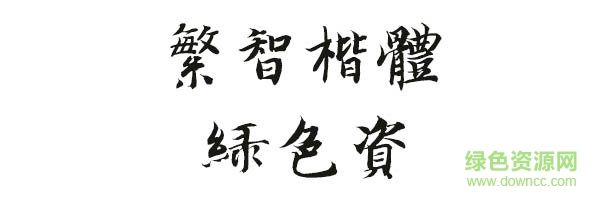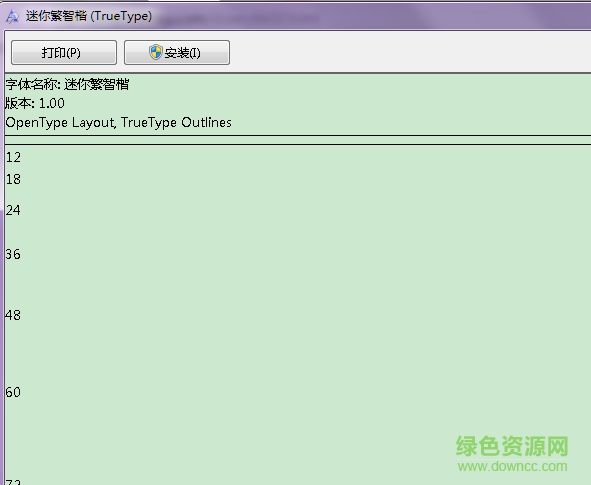
迷你繁智楷體字體是一款非??蓯鄣?a href="http://573ee.cn/k/xingkaiziti/" target="_blank">行楷字體,因為是迷你字型,所以比行楷更多可愛,有趣喲,需要該字體的朋友趕緊來綠色資源網(wǎng)下載吧
迷你繁智楷體為使用者呈現(xiàn)了一種端莊大氣的姿態(tài),給人心情舒適的感受,形如流水,非常具有觀賞性,實用與廣告設(shè)計等多個地方。